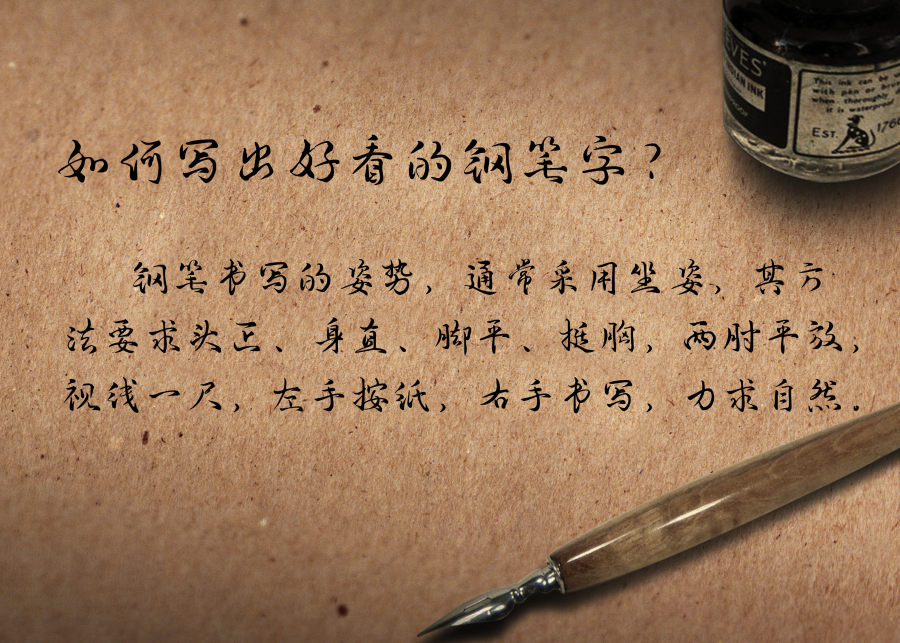
我们中华字体在几千年来的流传和传承下,从最初的甲骨文到现在的汉字简体,中间出现了一些可以彰显我们传统文化的字体,我们今天就要介绍的是其中的一个:新字行书,跟着我们一起看看吧。
行书是我们先人在日常使用的楷体的样本上进行提法研究出来的,没有草书的那么潦草难以辨认,也没有楷书的书写速度那么慢,使用性能非常高,是一种介于两者之间的独特字体。为了和古代创造的行书有所差别,印品字库公司团队中的设计人员开发出了新字行书,这一字体出世就受到了大众的喜爱。
我们使用新字行书一般是用来干嘛呢?无非是三种,第一种就是我们平常在互联网进行交流往来,进行文字沟通。第二种就是我们办公时使用,让我们自己看起来舒服或者让自己的办公文件有创意。第三种就是进行商业模式了,用字体进行商业化。